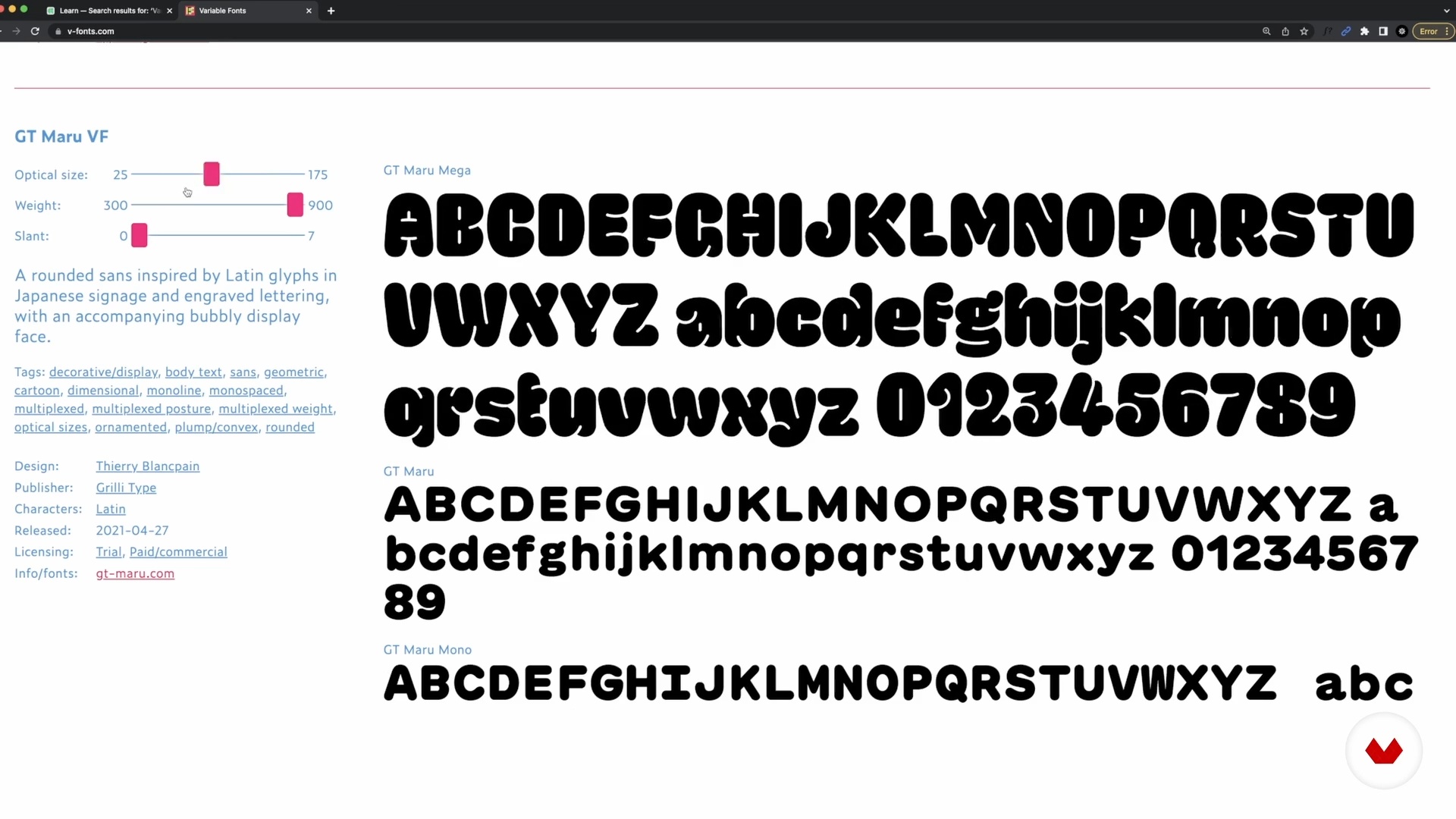
Diseño de logotipos variables (de inspiración popular)
Nuevos medios: tipografía variable 1
“Ahora que tienes las letras listas en un archivo de Glyphs, aprenderás a diseñar un segundo máster y con esto explorarás el mundo de los logotipos variables y entenderás para qué aportan desde lo técnico hasta lo visual. ”
En esta videolección, bastardatype aborda el tema: Nuevos medios: tipografía variable 1, que forma parte del curso online de Domestika: Diseño de logotipos variables (de inspiración popular). Descubre las técnicas más efectivas para diseñar logotipos variables únicos y atractivos..
“En esta lección vamos a hablar sobre logotipos y tipografía variable y de cómo esto nos va a dar mucha más identidad en nuestro proyecto. Les hemos dejado algunos links para que revisen y una fuente de nuestro estudio para que descarguen y también entiendan cómo es su funcionamiento. Recuerden que el nivel de experimentación depende de ustedes, así que esperamos que se reten. Vamos a seguir trabajando desde nuestro logotipo. Empecemos. En este caso, vamos a empezar con un logotipo de una serie de imágenes que se llama Los Pinos. Vamos a empezar trabajando desde nuestro logotipo. Empecemos. ...”